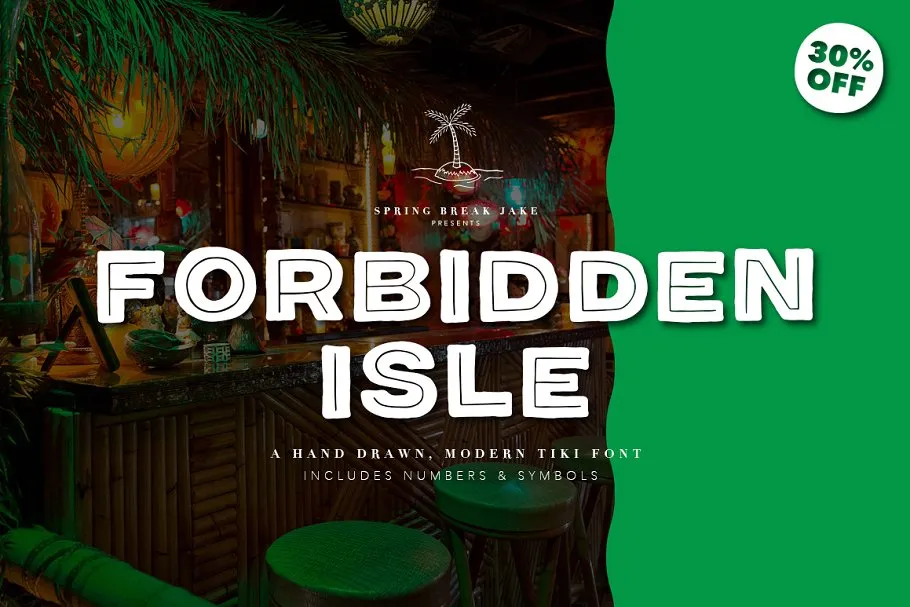
Forbidden Isle Tiki Font – Download Grátis
Descobrimos uma nova fonte chamada Forbidden Isle Tiki Font que traz o espírito dos anos 70 da tiki para a era moderna. Projetado por Spring Break Jake, essa é uma fonte premium disponível no Creativemarket. Para celebrar seu lançamento, está gratuitamente disponível para download hoje. Forbidden Isle toca em elementos icônicos do surfista tiki de décadas passadas, mas com um design limpo e bold que se adapta ao novo cenário visual. As imagens sugeridas são de barras feitas de bambu, fardos folgados de sabés e mugz desconcertantes. Esta fonte de tipo sem serif foi criada para expressar o amor que Spring Break Jake tem por tudo relacionado à tiki. Forbidden Isle se adequa bem tanto para tipos serifados quanto não-serifados, e pode dar vida a suas próximas ilustrações, convites, produtos e muito mais. A sua beleza singular torna-a uma fonte perfeita para qualquer projeto gráfico em que o seu estilo tiki seja essencial.